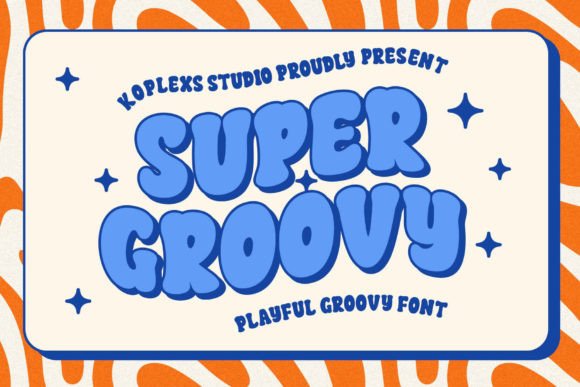
Super Groovy Font – أضف لمسة من الإبداع والمرح إلى تصاميمك!
استمتع بتصميمات مليئة بالحيوية والطابع الرجعي مع Super Groovy Font، الخط المثالي لمن يبحث عن مزيج فريد من الأناقة والمرح. يتميز هذا الخط بأسلوبه الجريء والمنحني، مما يجعله خيارًا رائعًا لتصميم الشعارات، العناوين، الملصقات، وسائل التواصل الاجتماعي، وأي مشروع يحتاج إلى طابع عصري مستوحى من السبعينيات.
✅ تصميم فريد يجمع بين الطابع الكلاسيكي والعصري
✅ مثالي للشعارات، الدعوات، العلامات التجارية، وغيرها
✅ يدعم الحروف الكبيرة والصغيرة مع رموز وأرقام متناسقة